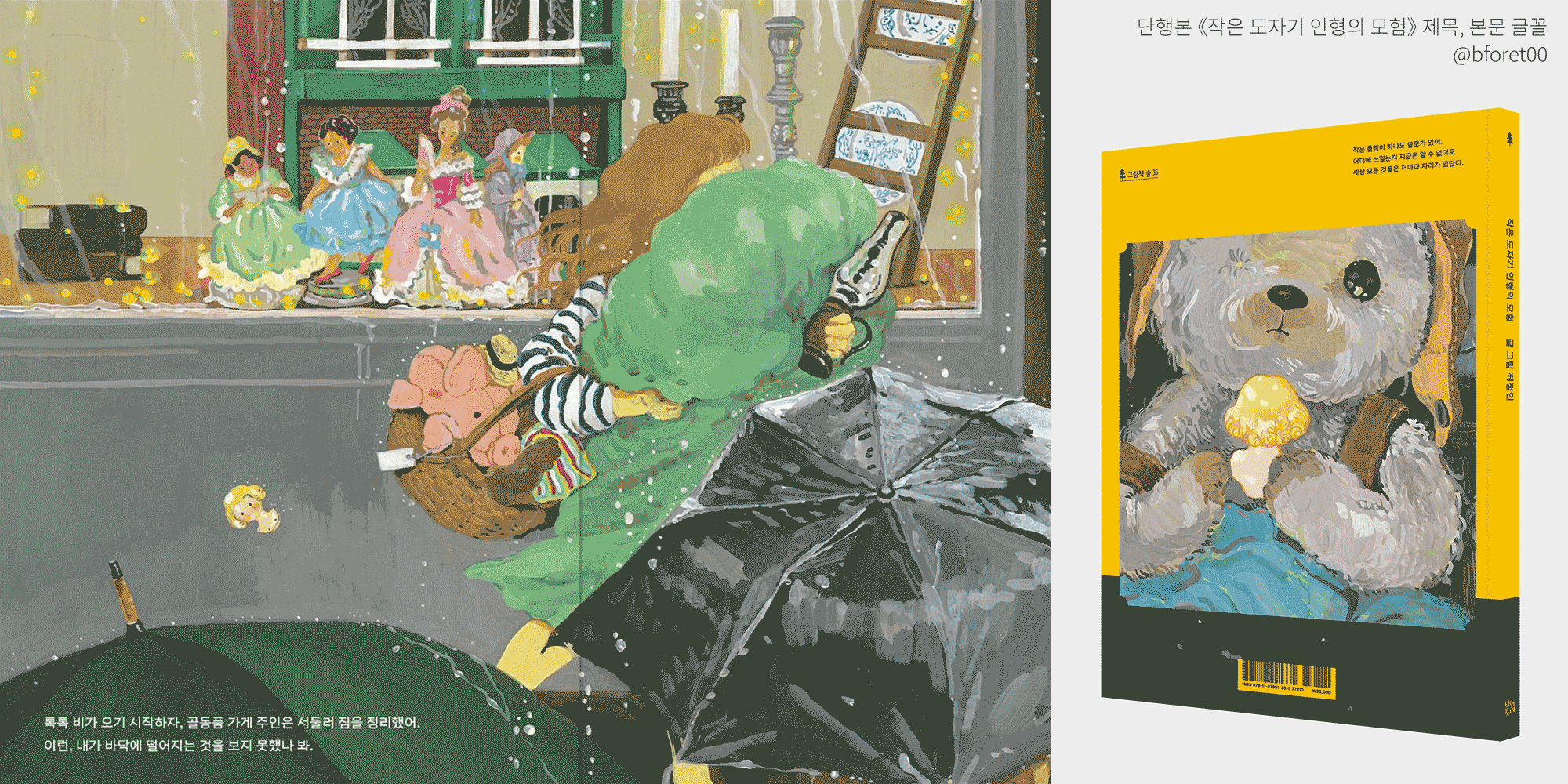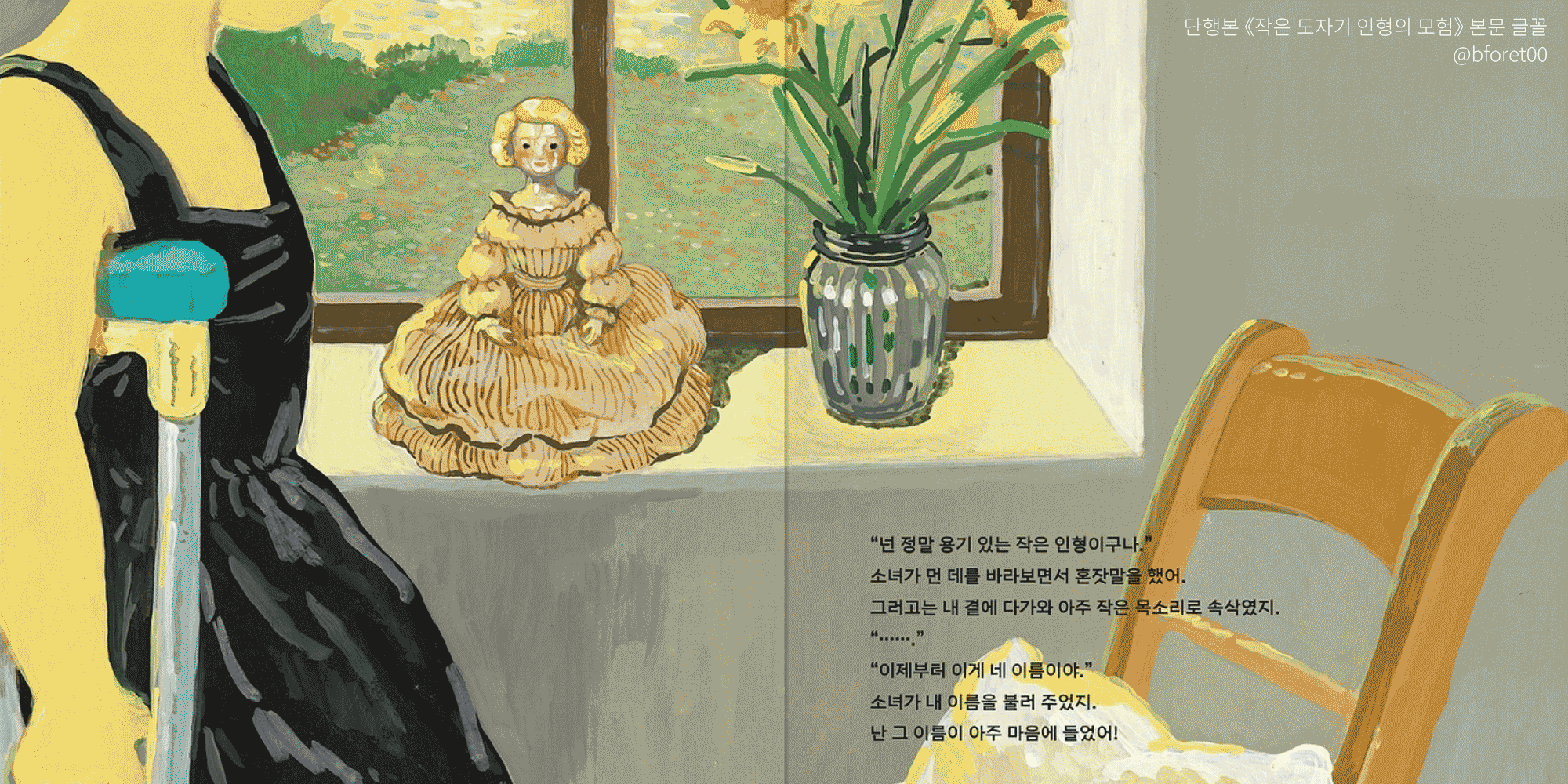
NormalGoshikku Family
노말고짓구 패밀리
〈노말고짓구〉는 1900년대 초반 광고에서 유행하던 ‘고짓구체’를 모티브로 하여 디자인한 디지털 글꼴입니다. 네모 틀에 꽉 찬 구조와 획의 끝부분을 날카롭게 처리한 부분이 특징이며, 다양한 장르의 제목(타이틀)으로 큼지막하게 쓰였을 때 더욱 돋보입니다. 미디엄(Medium)과 볼드(Bold) 2종으로 구성되어 있어 쓰임새가 다양합니다.